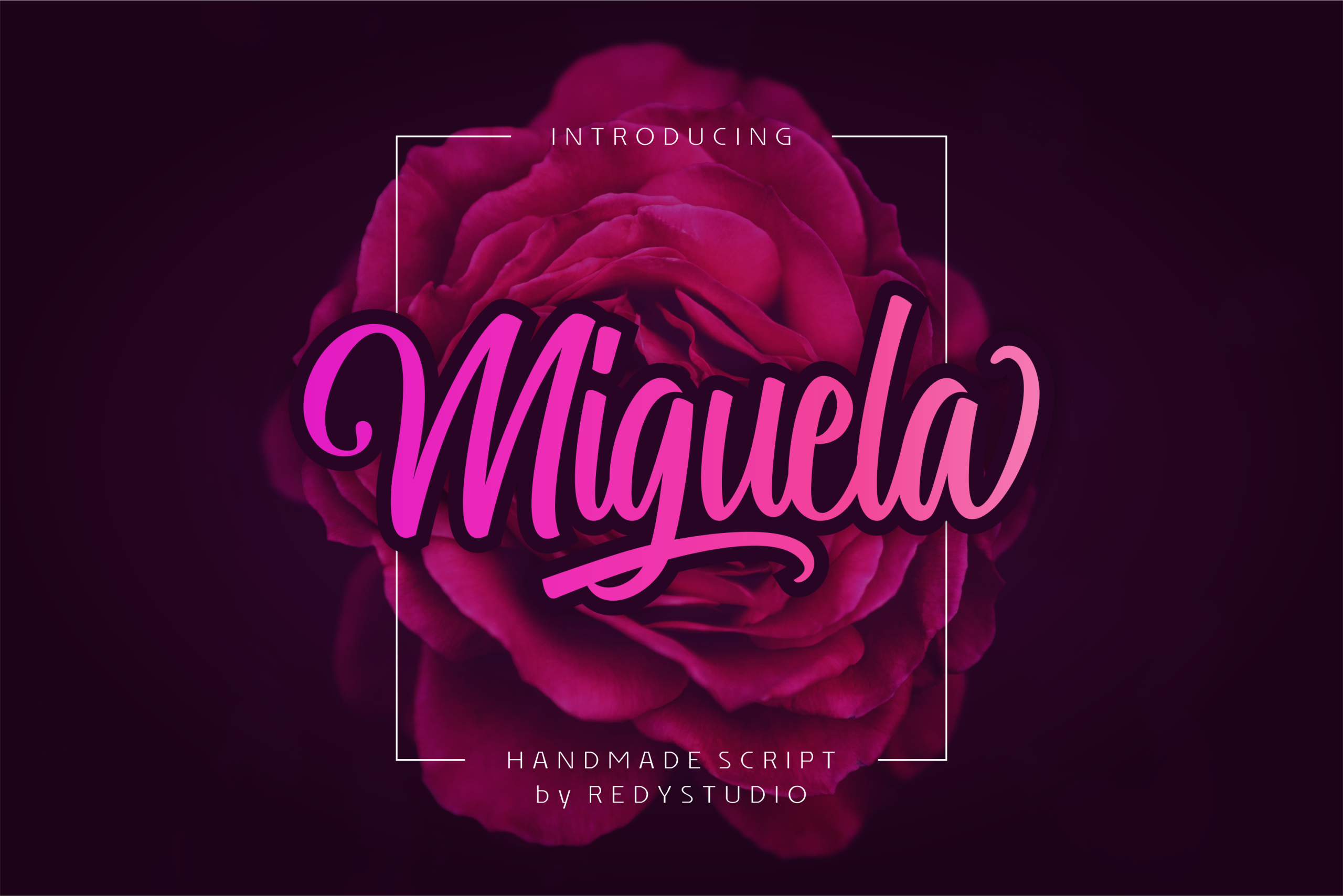
Miguela Script Font – Download Grátis
Introduzimos Miguela, uma nova fonte casual script cuidadosamente criada para fornecer um fluxo dinâmico. Ela foi concebida pensando no seu uso imediato para criar belos designs de letra e tipografia. Miguela é perfeita para sua necessidade de projetos criativos como logotipos, citações impressas em cartões, embalagens de produtos, cartão da carta, postais, design de roupas e mais. Com um conjunto abrangente de letras maiúsculas e minúsculas, pontuação, números e diversas variações para cada caractere, incluindo alternativas do OpenType que lhe permitem personalizar suas criações conforme necessário. Miguela é uma escolha ideal tanto para aqueles buscando um pouco mais de diversão em seus projetos como para os que desejam algo mais sofisticado. Sempre disponível e extremamente versátil, Miguela é sua fonte perfeita para todos os seus projetos.
Designer: RedyStudio